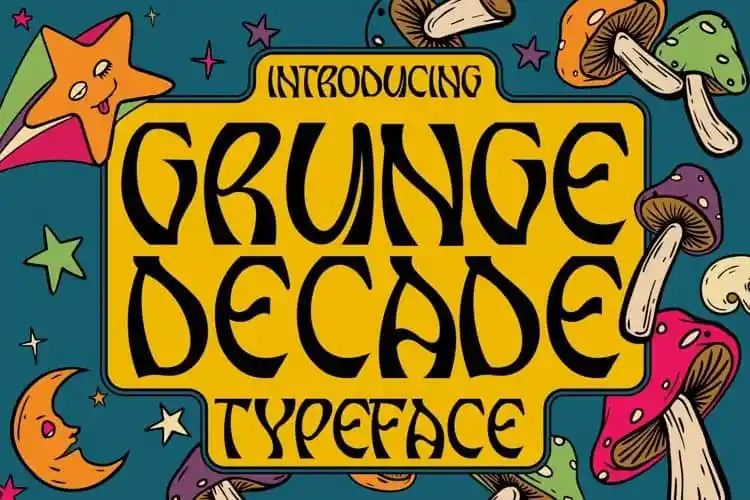
Grunge Decade Display Font
A fonte Grunge Decade Display é uma criação criativa e vibrante de Alit suarnegara, inspirada nos estilos visuais dos anos 80. Com um charme único e personalidade inconfundível, esta elegante serifada foi concebida para aqueles que buscam algo diferente em suas criações digitais. Inspirada no design visual da década de 1980 para as plantas de cogumelos mágicos, uma tendência que se tornou popular nesse período, a fonte incorpora elementos divertidos e sem ser sério, mantendo o valor estético e único. Gratificante por sua facilidade de memorização, Grunge Decade Display é perfeita para designers procurando uma imagem distintiva. Com um design que se adequa tão bem aos ambientes digitais modernos, esta fonte oferece uma maneira única de destacar suas criações enquanto mantém o foco nas experiências visuais atraentes e memoráveis.